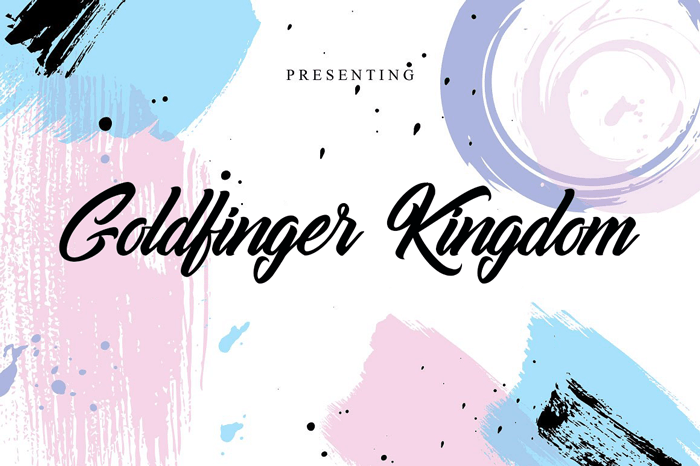
Goldfinger Kingdom Font – Download Grátis
A Octotype lançou uma nova fonte chamada “Goldfinger Kingdom Font”, categorizada como ‘Calligraphy Fonts’. Esta fonte oferece uma gama completa e licença comercial para quem deseja utilizar ou vender a mesma. Os detalhes de compra estão disponíveis em . A Goldfinger Kingdom Font é uma grIFE única, com linhas finas e traços exuberantes que permitem criar rótulos bonitos, textos elaborados e logotipos distintivos. Seja para uso pessoal ou comercial, esta fonte traz um toque de luxo à sua produção. Com Octotype, você tem a garantia de alta qualidade e precisão na impressão. Prove Goldfinger Kingdom Font agora mesmo!